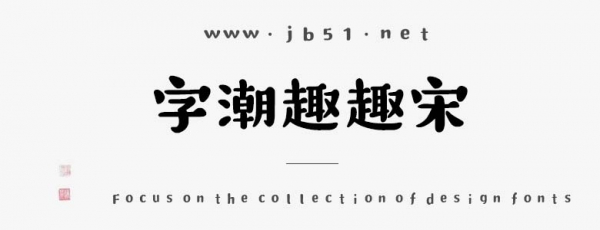
字潮趣趣宋是由字潮字庫(kù)出品的字體,這款字體筆觸適中,字形端正,略顯圓潤(rùn),具有很好的視覺感,適合應(yīng)用于藝術(shù)設(shè)計(jì)、平面宣傳設(shè)計(jì)、網(wǎng)頁(yè)設(shè)計(jì),書法字帖等領(lǐng)域,需要的朋友可以前來本站下載。